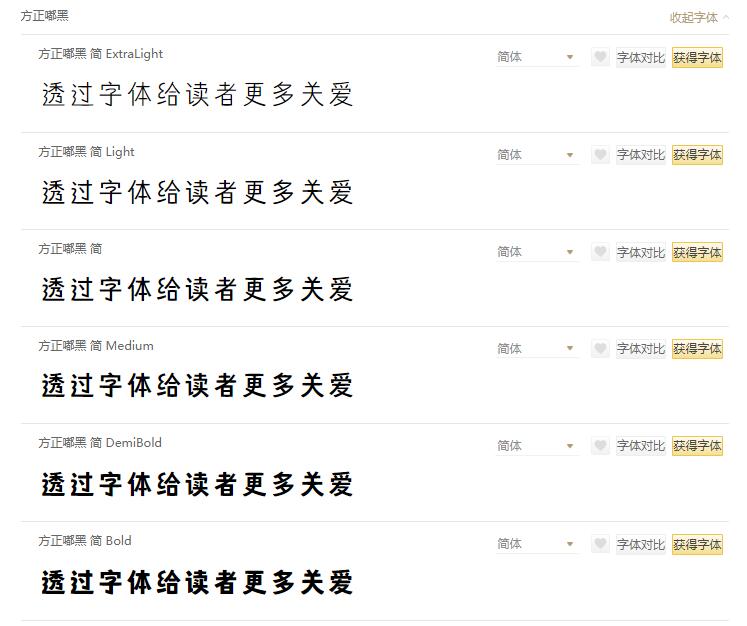
方正嘟黑體簡(jiǎn)一款不錯(cuò)手繪字體,該系列字體共六款,字體書寫端正大氣,具有很好的視覺(jué)感,適合應(yīng)用于藝術(shù)設(shè)計(jì)、平面宣傳設(shè)計(jì)、網(wǎng)頁(yè)設(shè)計(jì),書法字帖等領(lǐng)域。
該系列字體
方正字庫(kù)簽約設(shè)計(jì)師、深圳市平面設(shè)計(jì)協(xié)會(huì)會(huì)員、重慶工商大學(xué)現(xiàn)代國(guó)際設(shè)計(jì)藝術(shù)學(xué)院客座教授。方正嘟黑在黑體筆形基礎(chǔ)上融入了楷書的筆意,具有書寫感。字體線條剛?cè)岵?jì),稚拙而有生活氣息